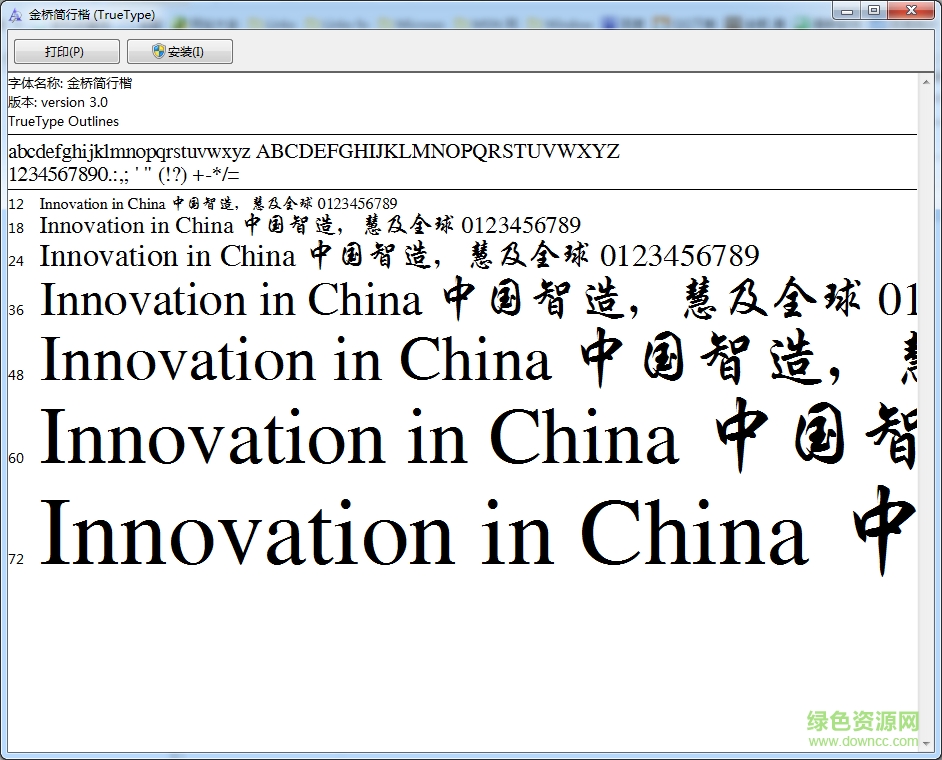
jqxingkaijt字體也就是金橋簡(jiǎn)行楷字體,這款字體筆畫灑脫,筆鋒細(xì)膩,完美闡釋了行楷酷炫風(fēng)格,深受廣大書法家喜愛,適應(yīng)于排版設(shè)計(jì)、廣告創(chuàng)意、印刷等領(lǐng)域,需要的朋友歡迎來綠色資源網(wǎng)免費(fèi)下載使用。
jqxingkaijt字體是一款常用的行楷字體,這款字體融合了行楷兩大字體的元素,展現(xiàn)出一種行書的凌厲,很具觀賞感性,字體飄逸灑脫,行筆流暢自然,喜歡這款字體的朋友歡迎來綠色資源網(wǎng)下載體驗(yàn)!